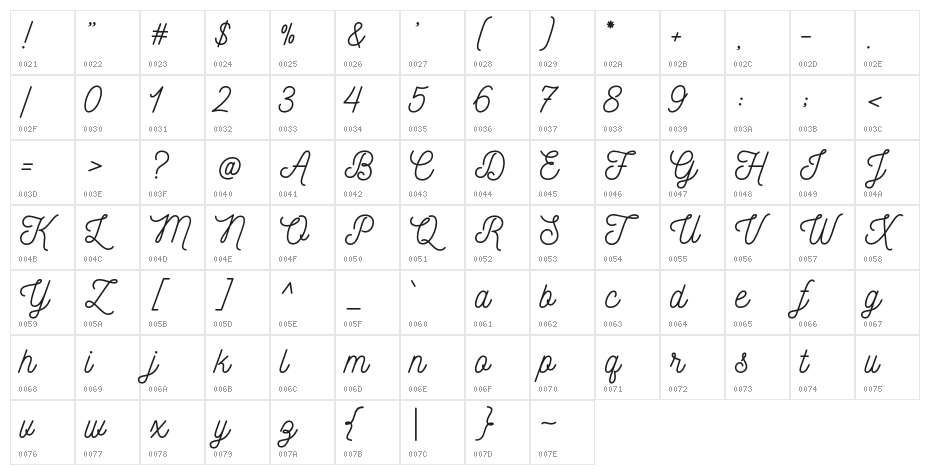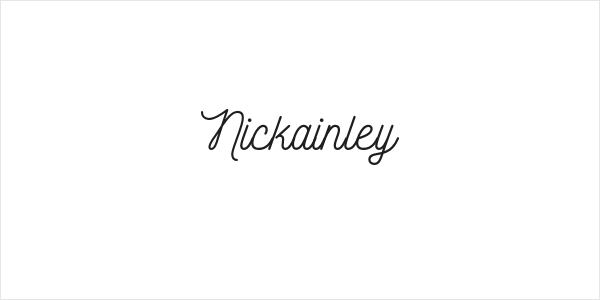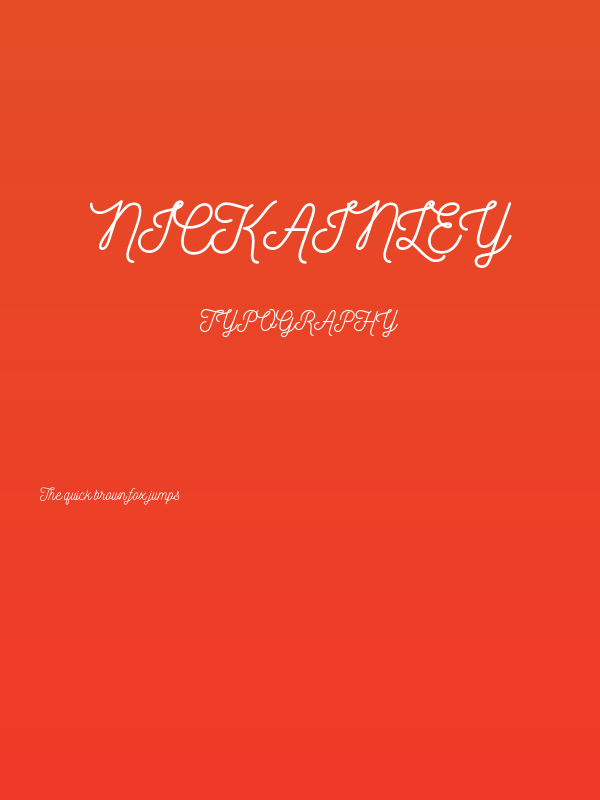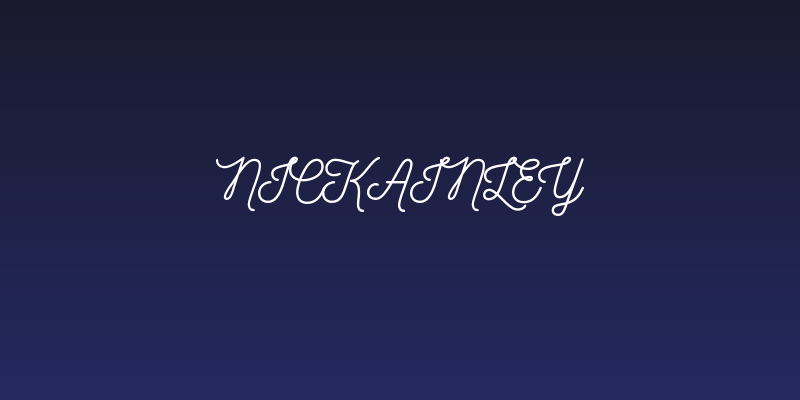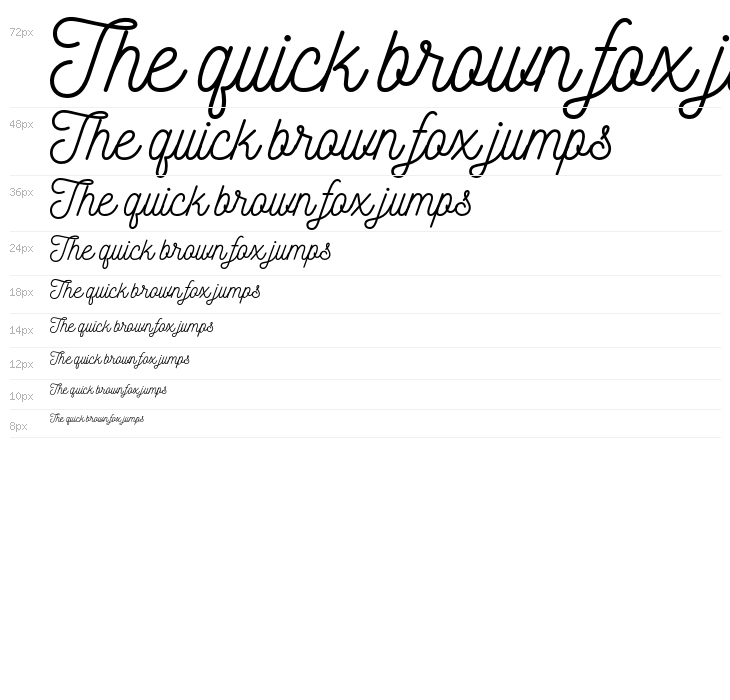
Nickainley Font
| Gesamtstil | Elegant |
| Anwendungsfall | Logos, Invitations, Personal Branding |
| Vorgeschlagene Projekte | Ideal for wedding invitations, greeting cards, personal branding, and elegant packaging. |